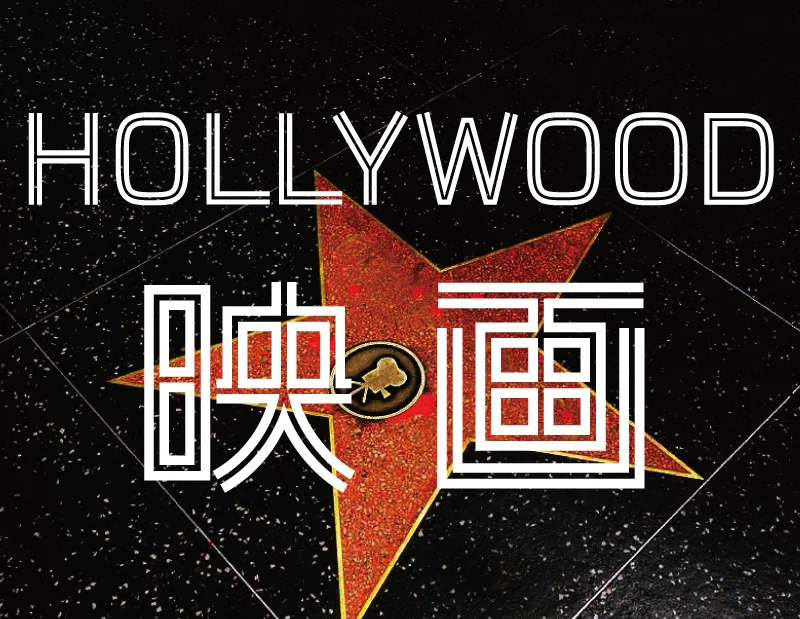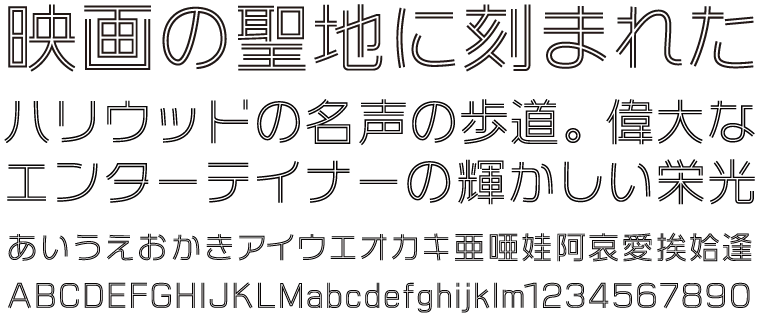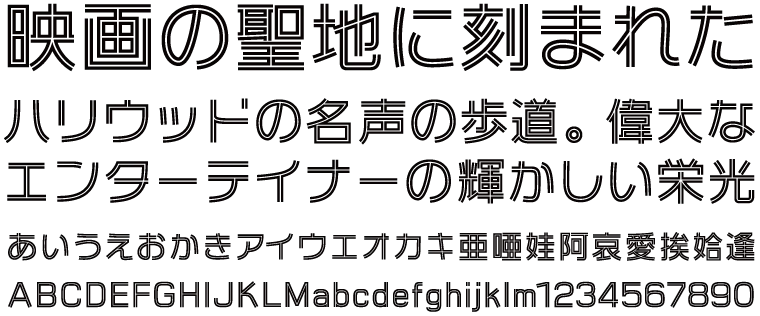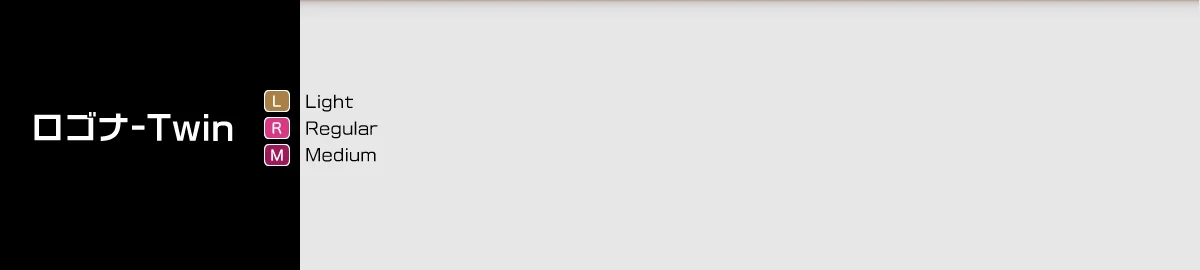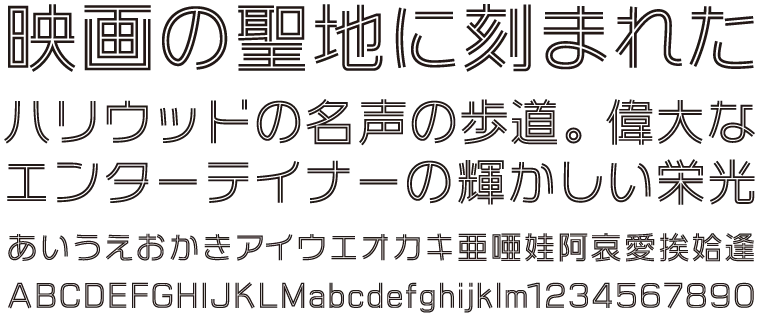
ロゴナ-Twinの特徴
「ロゴナ-Twin 」は、「ロゴナ」のデザインをベースにした新ジャンルの書体ファミリーです。グリフの中央にラインが貫通したTWIN構造で、複雑なエレメントは意図的に省略してバランスと可読性に配慮しました。画数の多い文字も潰れがなく、清楚で引き締まった都会的センスの進化形ゴシック体です。